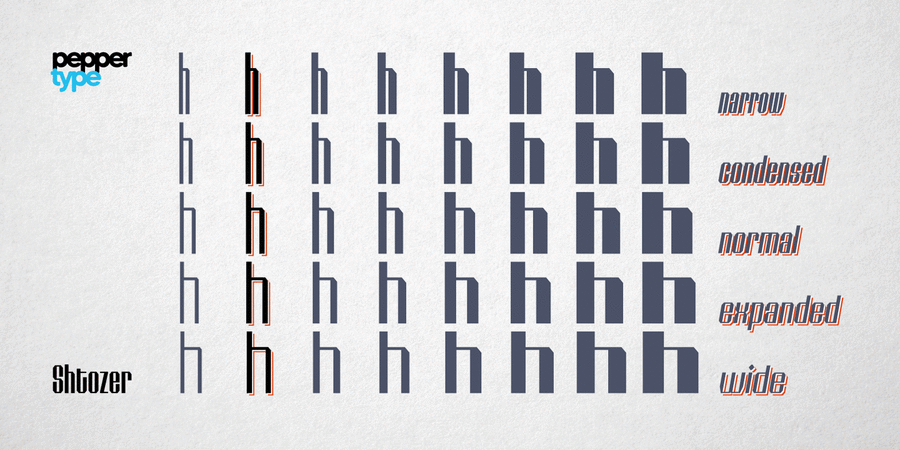
Опис гарнітури Shtozer 200Слабоконтрастна версія шрифту Штозер. Акцидентний шрифт у стилі ретро, створений за мотивами 1960-х і 1970-х років, додатково натхненний кириличної в'яззю. Він поставляється у 8 насиченостях, з 5 варіантами ширини для кожної, все супроводжуються відповідними нахиленими версіями – в цілому 80 накреслень. Shtozer – шрифтове сімейство з широким мовним охопленням, що включає кирилицю. Гарнітура також містить безліч функцій OpenType і альтернативних ґліфів для пожвавлення набору. Шрифт розробив Олег Ліщук у 2020 році.
Особливості сімейства шрифтів Shtozer 200Хіт десятиліття:
Асоціації з сімейством шрифтів Shtozer 200Особистість і характер гарнітури:
комп'ютерний, електронний, молодіжний, рівний, точний, логічний, автоматичний, техногенний, твердий, статичний, різкий, чіткий, стійкий, стабільний, прямокутний, міський, сучасний, машинний, інженерний, урбаністичний, креслярський, сталевий, індустріальний, залізний, мужній, промисловий, футуристичний, ламаний, незграбний, помітний, кінематографічний, ритмічний, гучний, тісний, потужний, гострий, високий, важкий, худий, стрункий, ігровий, строковий, стиснений, холодний, квадратний, характерний, економний, штучний, архітектурний, космічний
комп'ютер, конструктор, креслення, інженер, автоматика, урбаністика, електроніка, авто, інструмент, робот, гра, техніка, прилад, автомат, технології, андроїд, залізо, фантастика, кіно, лего, іграшка, кубики, хмарочос, кінотеатр, архітектура, комп'ютерна гра, гаджет, девайс, верстат, промисловість, Місто, космос, зореліт Гарнітура асоціюється з віком: